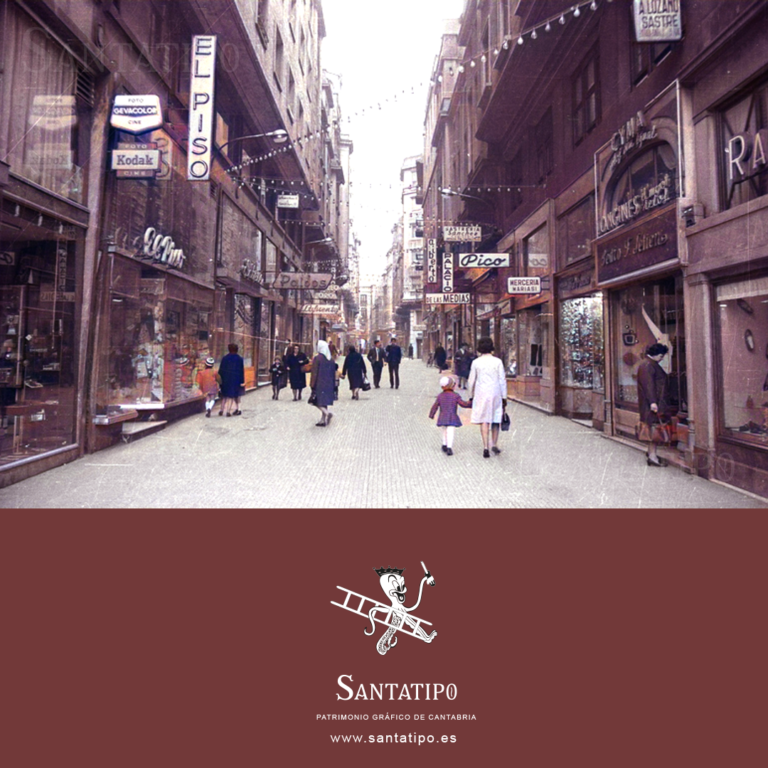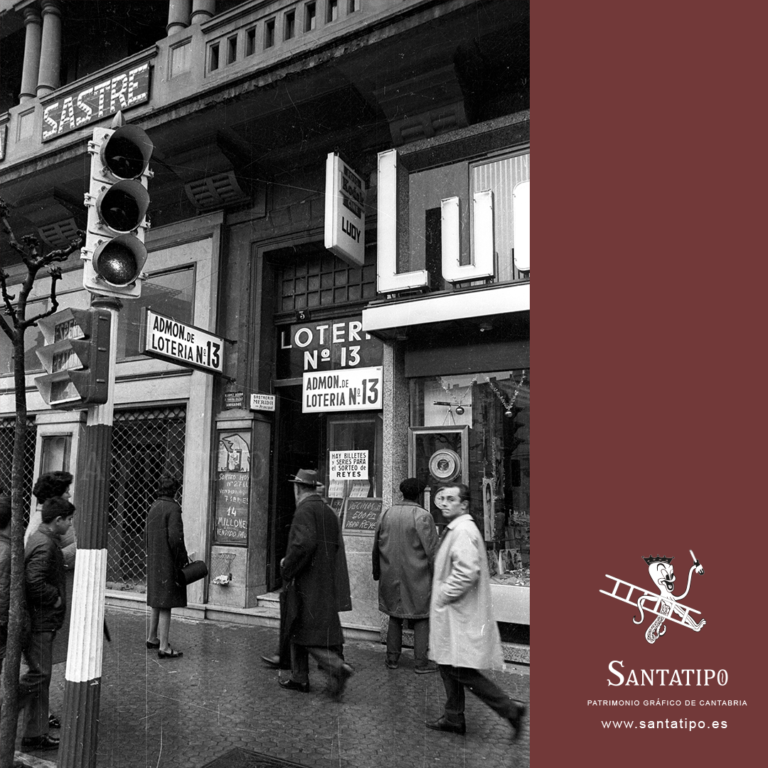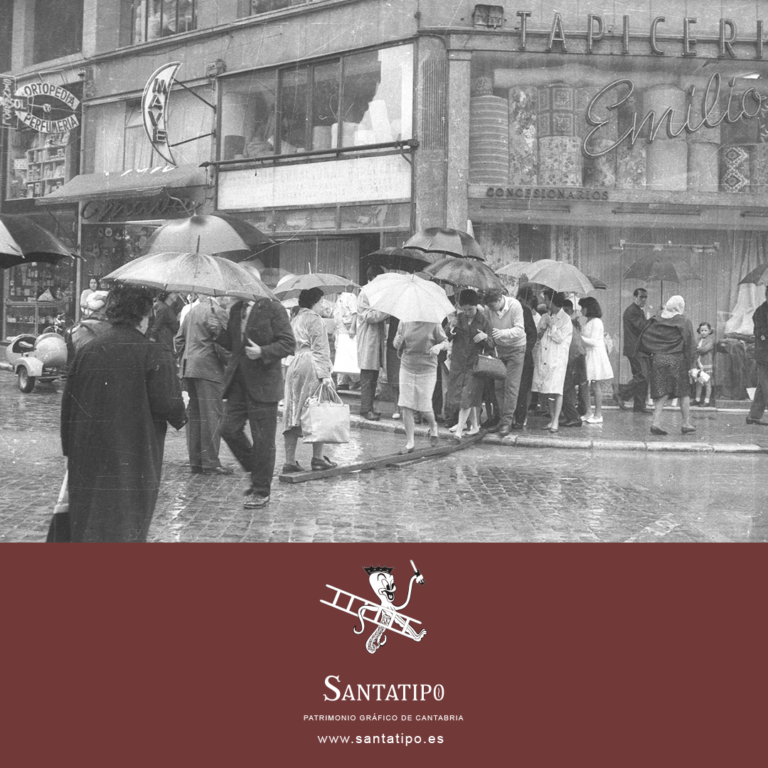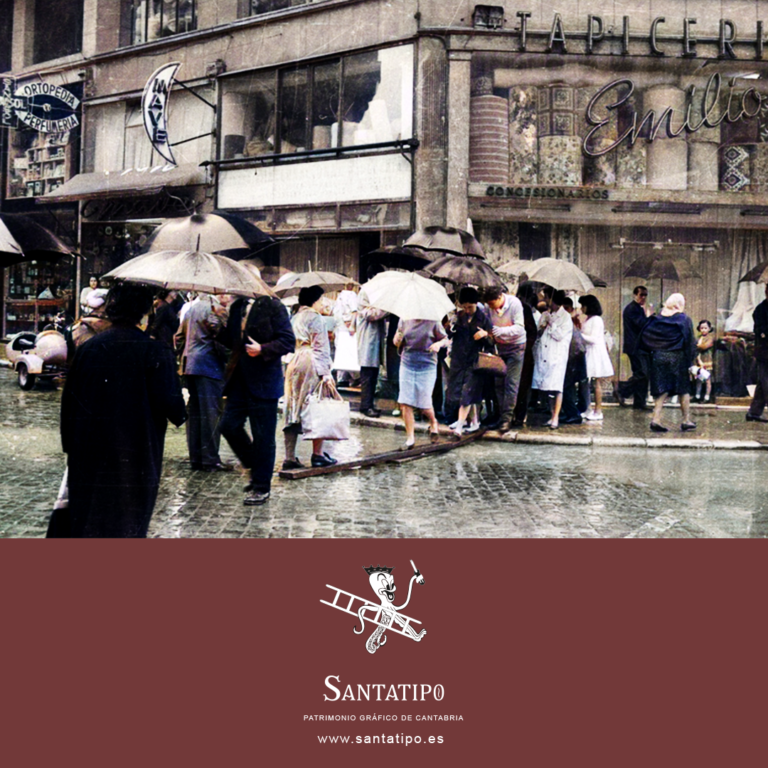
Recuperando el color
Desde Santatipo, nos gusta seguir investigando y trabajar en la recuperación del Patrimonio Gráfico de nuestra región. Aparte de documentarlo in situ, trabajamos con los archivos fotográficos. Y es ahí, donde también queremos saber como podría ser la imagen de ese pasado. Gracias a las nuevas técnicas, podemos recuperar parte de ese color dentro del Blanco y Negro, que nos ayuda a entender conceptos visuales en la fabricación de rótulos y cartelería comercial.
Esta es una pequeña muestra de lo que iremos haciendo paulatinamente.